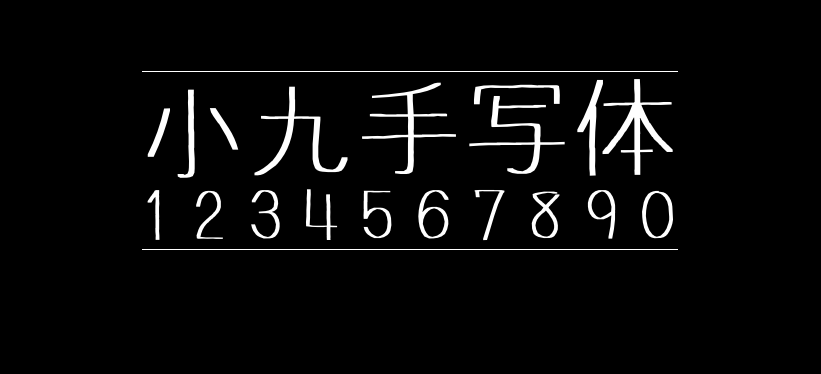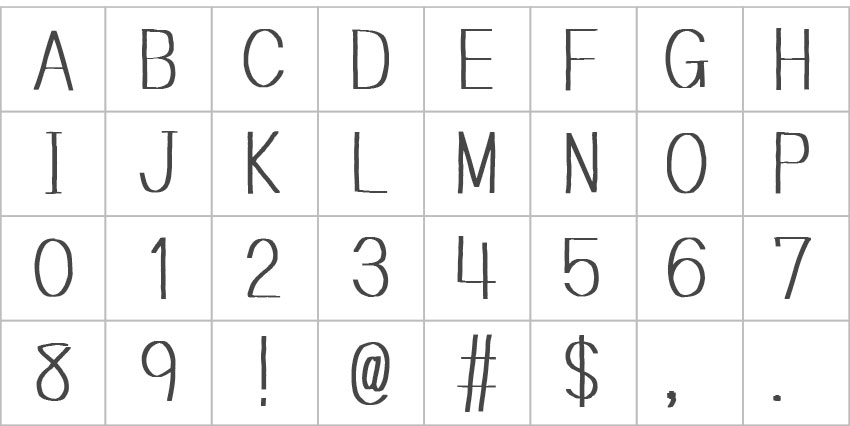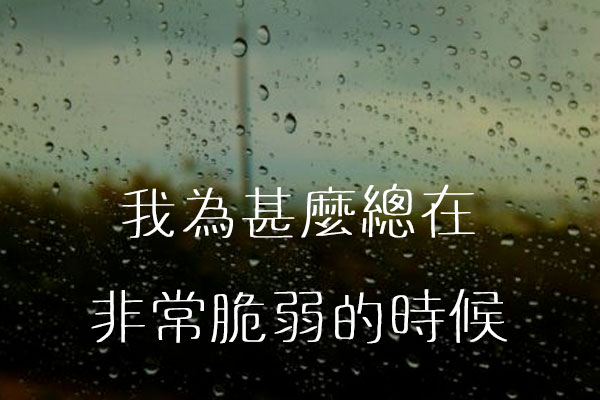
小九手写体
小九手写体(九ちゃんフォント Kyuchan)是日本字体作者隠れ家创作的一款笔画非常幼细的字体。字体的风格纤细,就像女孩子写的字体,特别适合用于女性,儿童,偏可爱风格的海报设计。可以作为正文文字和印刷物等的素材使用。这款字体是日本的设计师发布的字体,所以字符是以JIS为标准的,所以对繁体支持较好,简体字相对少一些。